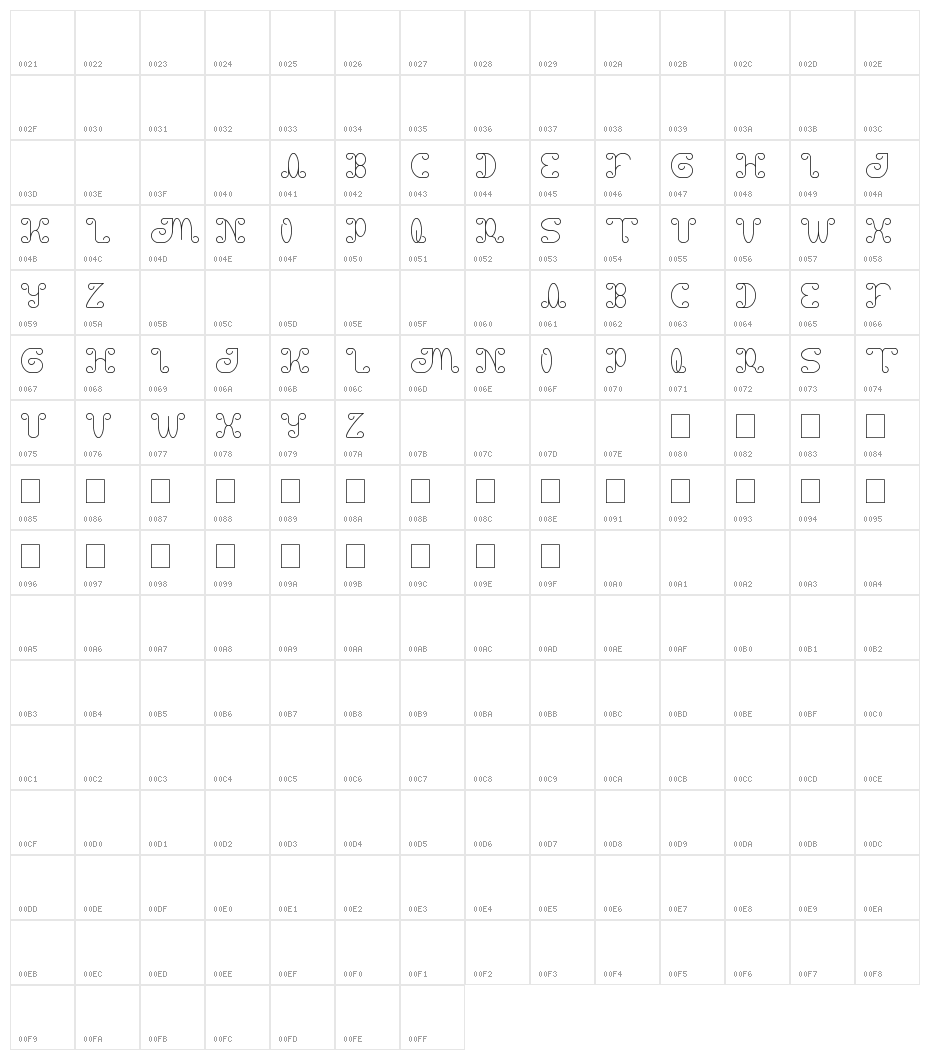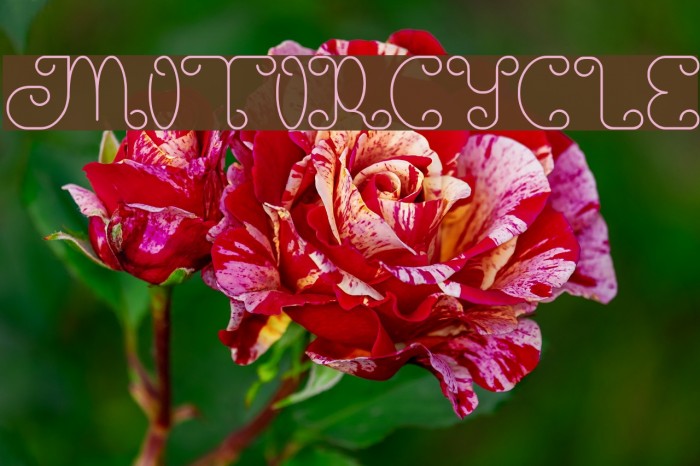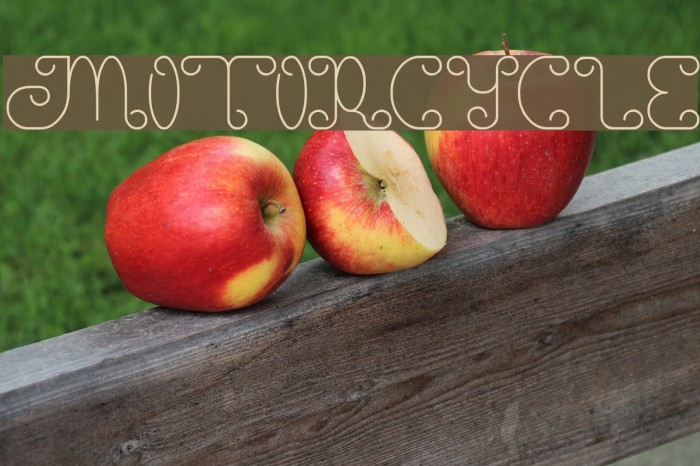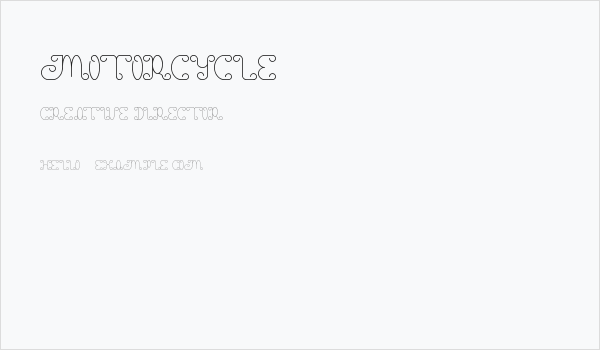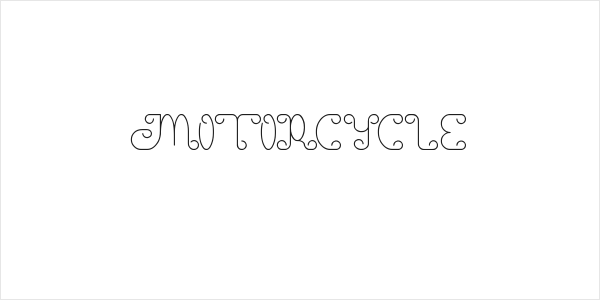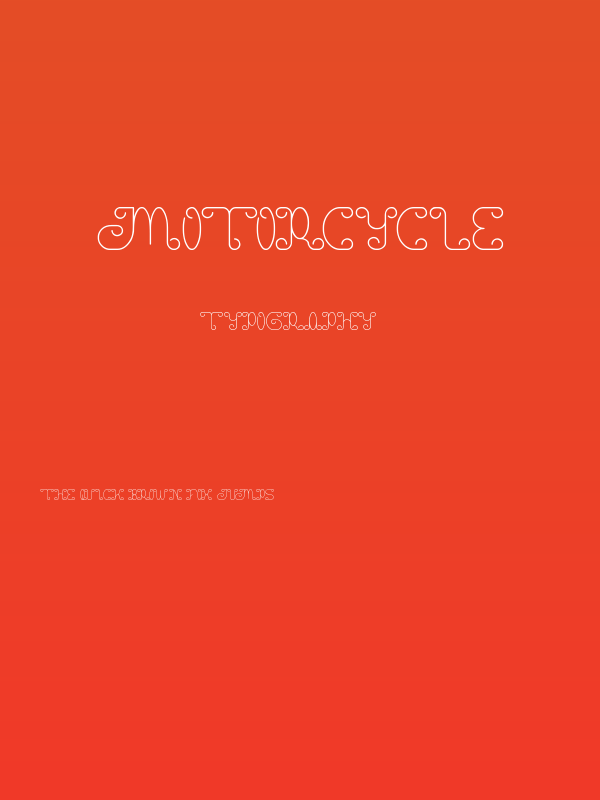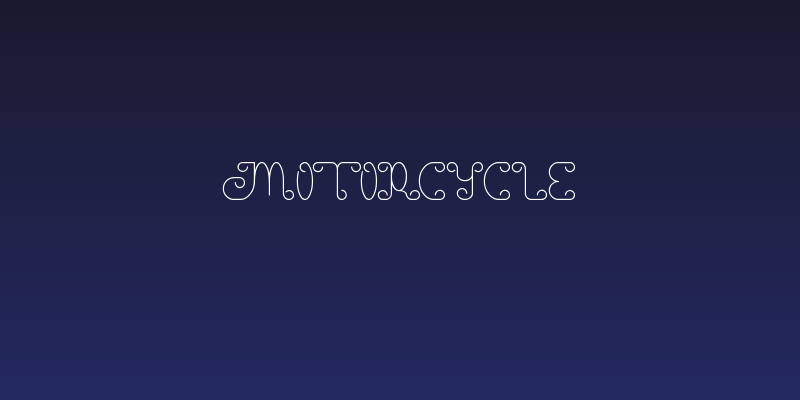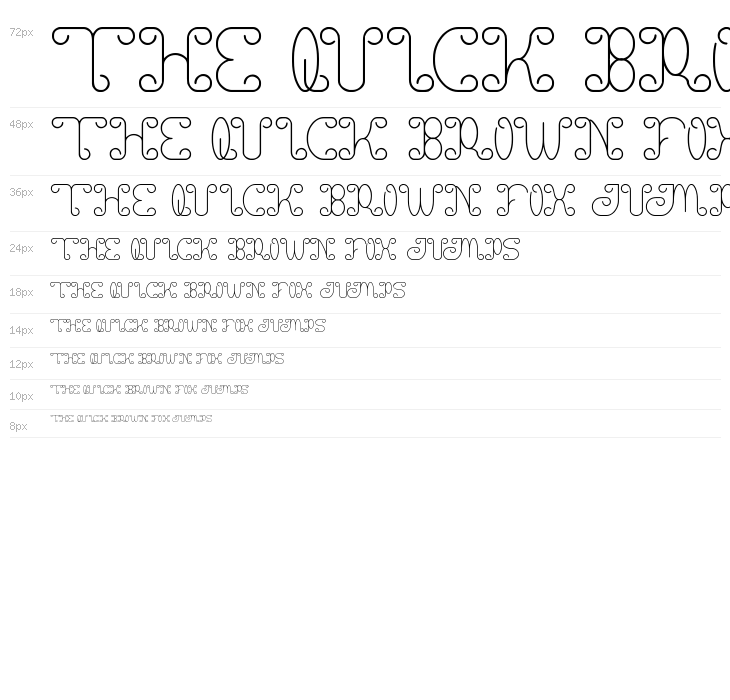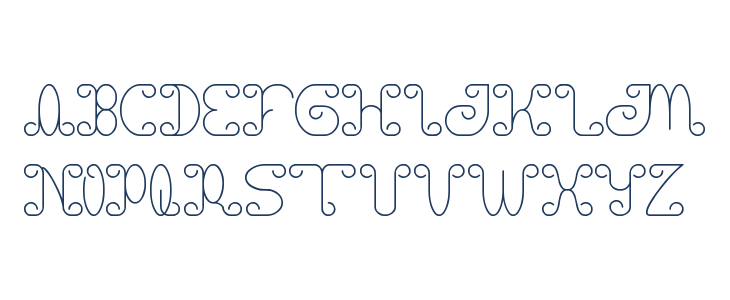
motorcycle Font
| Caso d'uso | Logos, Invitations, Artistic Projects |
| Progetti proposti | Ideal for wedding invitations, greeting cards, artistic posters, and branding that requires a creative and elegant touch. |